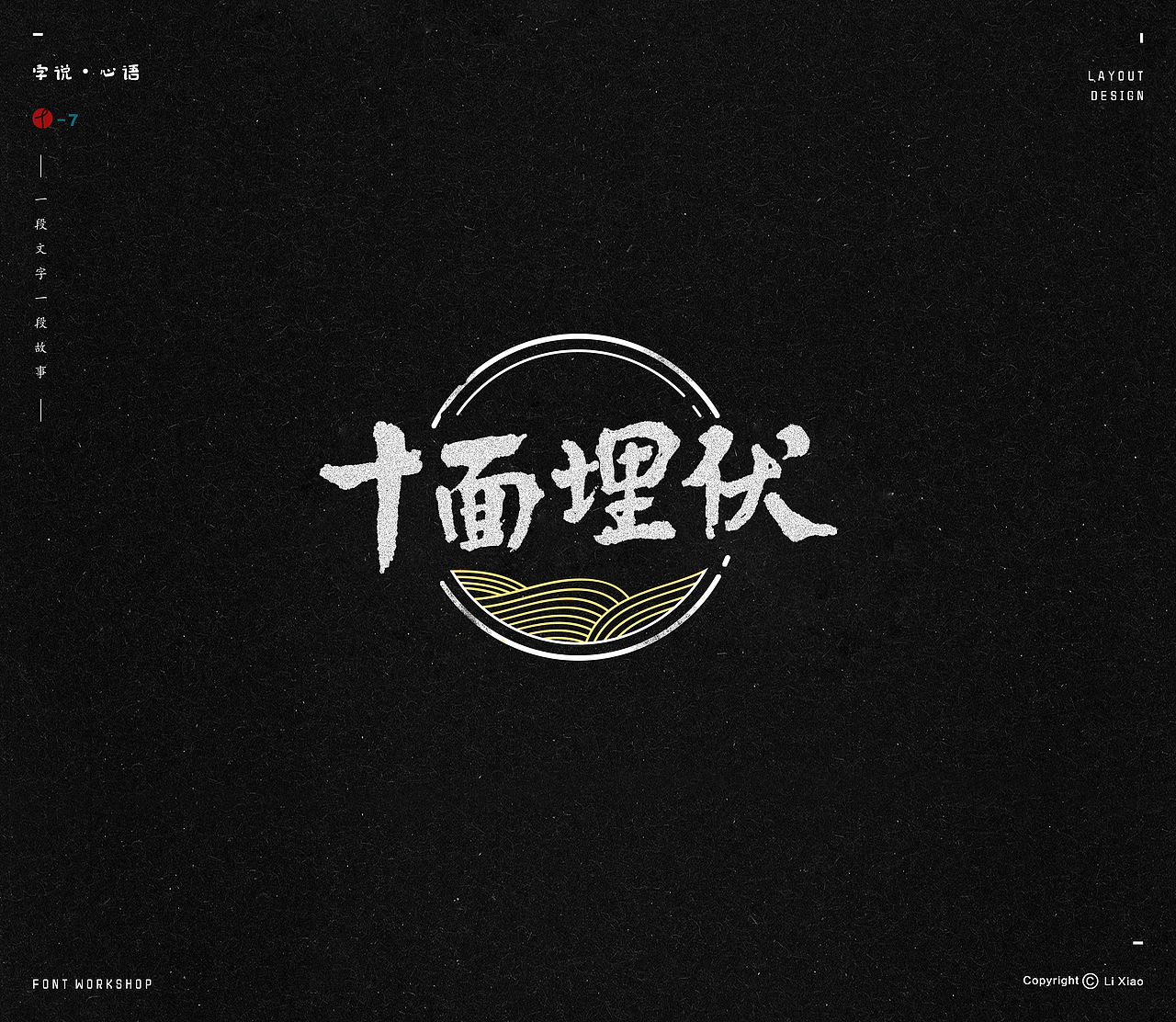
涂涂画画、练练书法、写写随笔,拍拍照片、做点小设计、品诗论画、走走逛逛……
理想中的“文艺青年的日常”无外乎如此了,however,我不是理想主义者,回归现实、好好工作。
整理了一些书法练习,取材来源于一些歌名、歌词、词牌名、诗句、格言、剧名、电影台词……并融合了一些自己的生活感悟。
album cover redesign / font design / layout design / illustration (practise)
鸡年大吉
元宵节贺图
轻蔑
伊人如梦
失恋的人不能听
白头吟
十面埋伏
半糖主义
凤囚凤
鱼趣
煎熬
伊人如故
且行且珍惜
觉悟
凤头钗
魂归旧处
人去茶凉
可不可以不忧伤
哭泣的皮皮虾
大鱼海棠
莲心
知足常乐
那些年,我们都追过的偶像
三生三世十里桃花
只有我自己